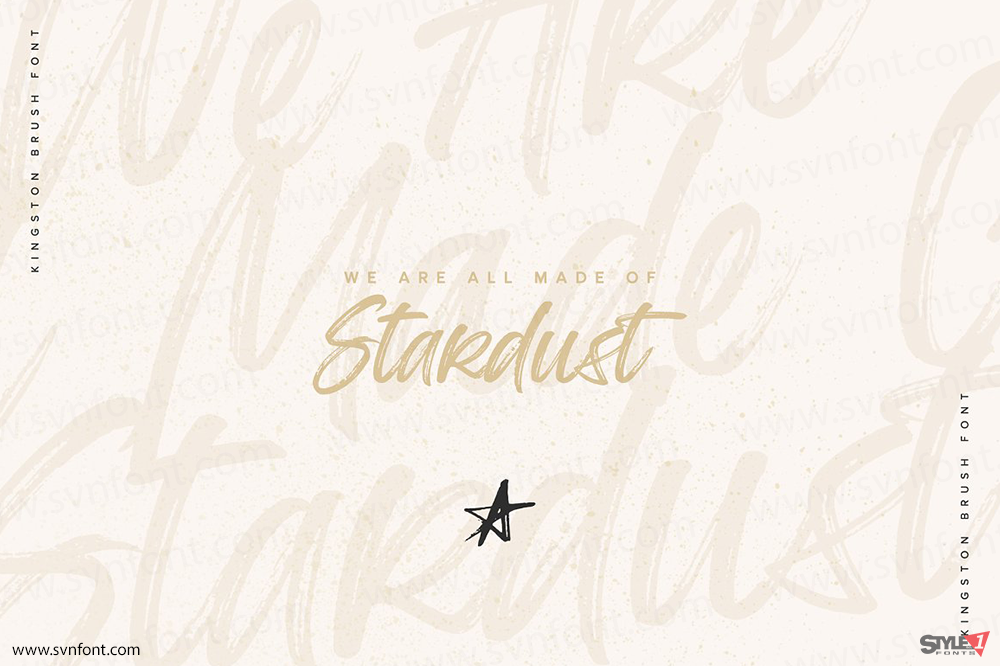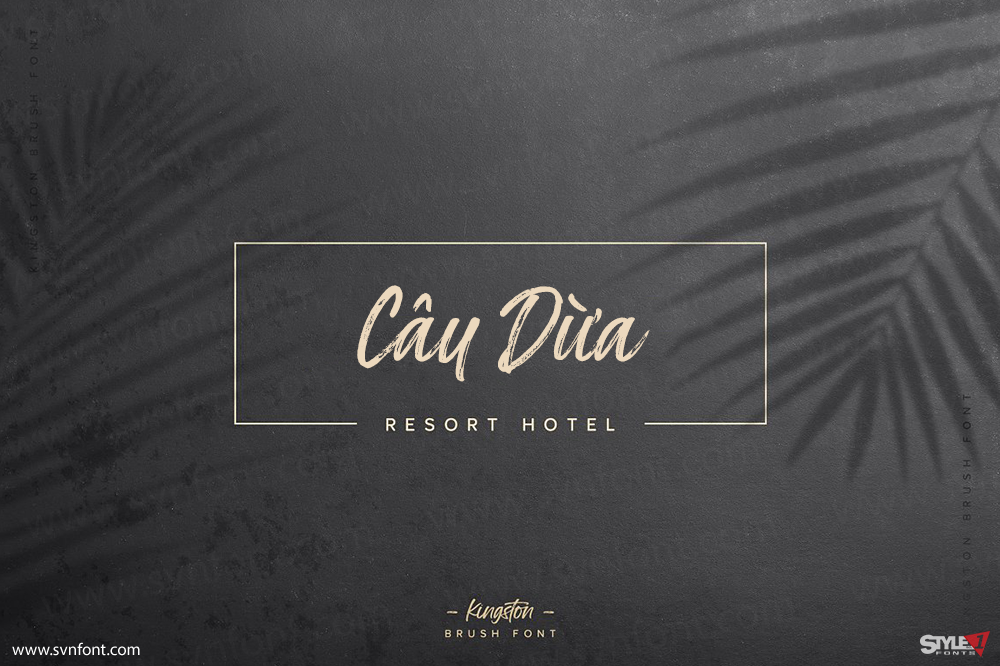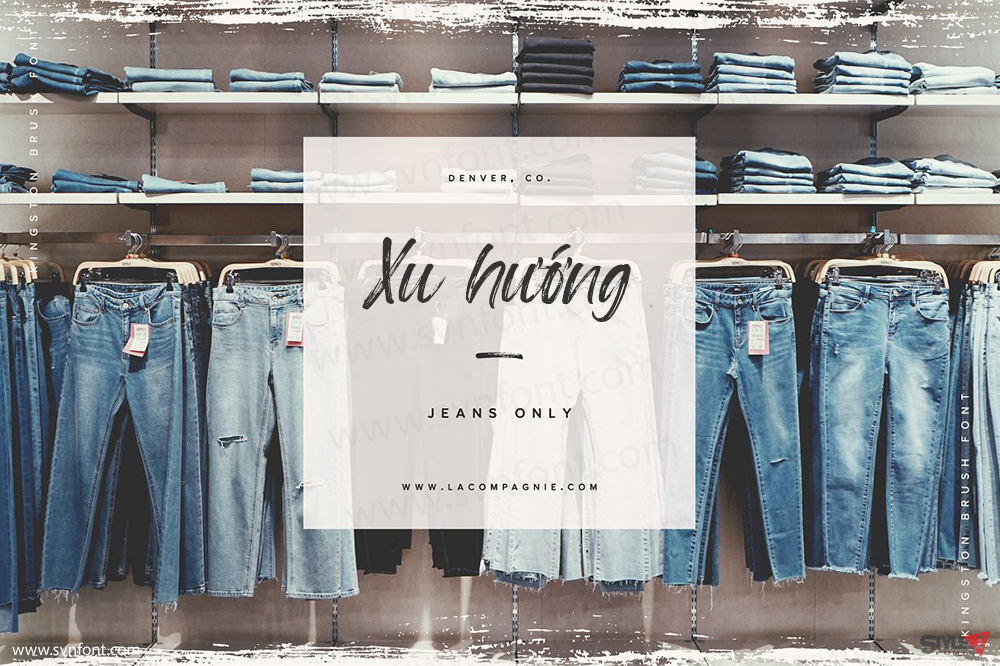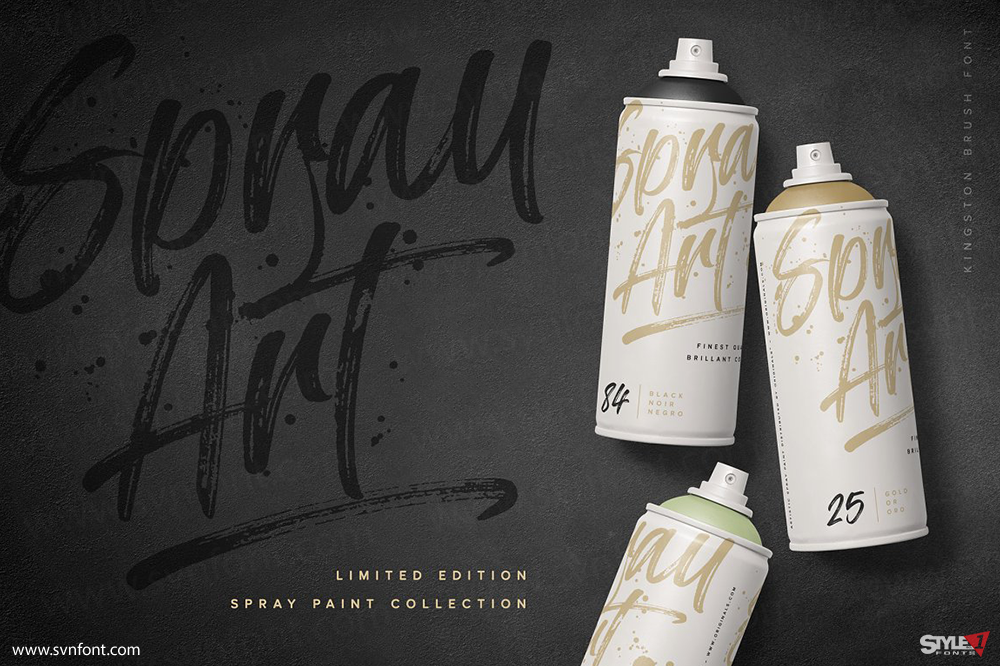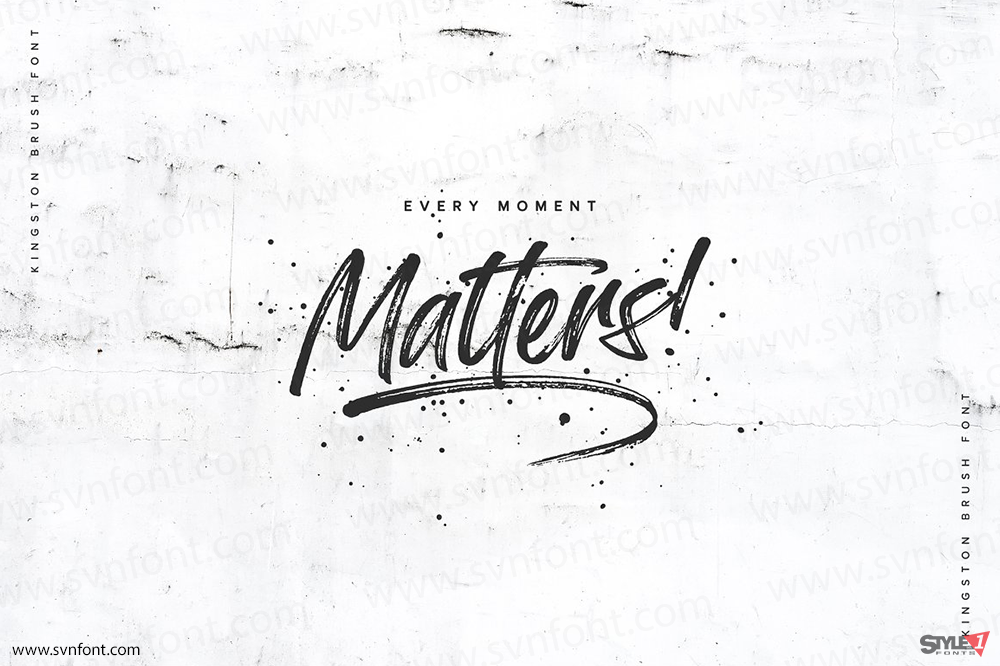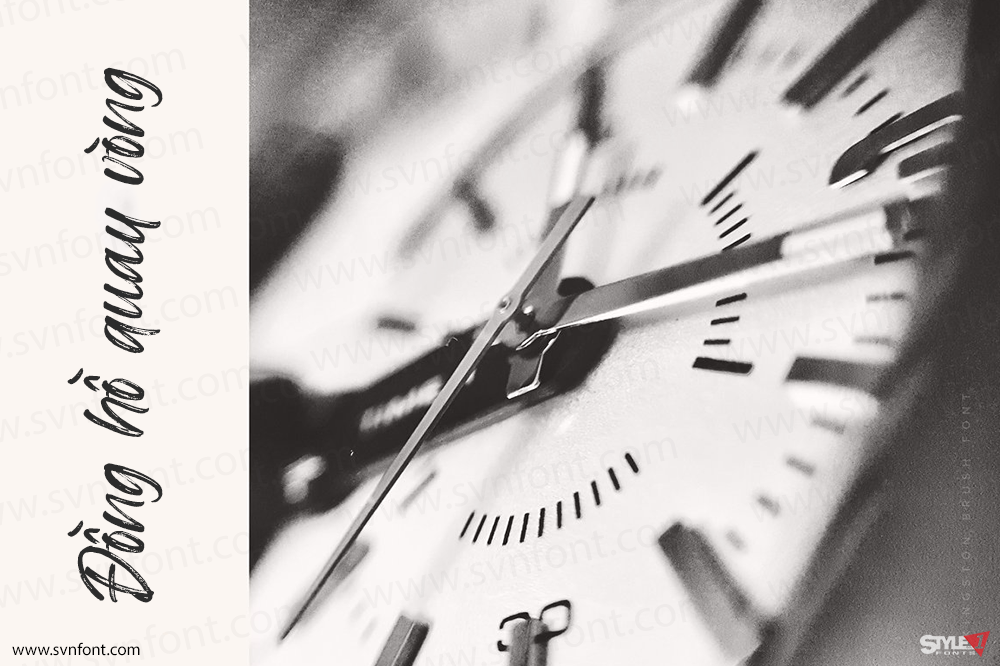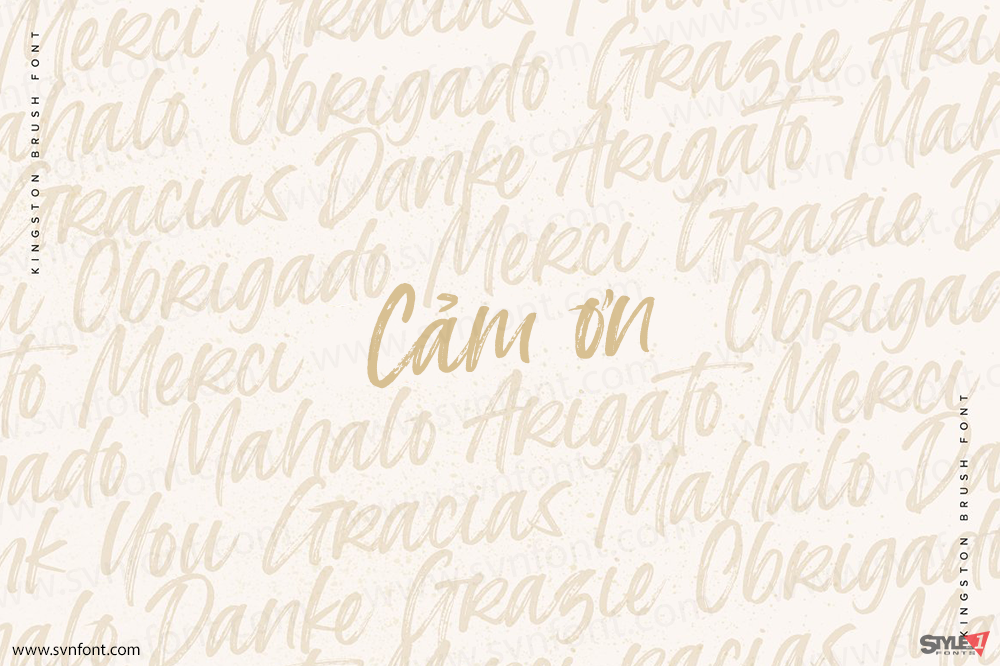
Giới thiệu Kingston, một font chữ viết tay với kết cấu cọ khô cực kỳ chi tiết. Kingston đã được thiết kế để phù hợp với nhiều loại dự án, từ phong cách đô thị đến xây dựng thương hiệu cổ điển, với một bộ ký tự thay thế đầy đủ để thay đổi hoàn toàn giao diện thiết kế của bạn.
Kingston cũng bao gồm một bộ gồm 52 yếu tố vẽ tay sẽ thêm một nét hoàn thiện đẹp mắt cho văn bản Kingston của bạn. Bạn có thể sử dụng nó cho xây dựng thương hiệu doanh nghiệp, trích dẫn Instagram, tiêu đề blog, thời trang, văn phòng phẩm và nhiều hơn nữa…
Nhà thiết kế: The Paper Town
Nhà phát hành: The Paper Town